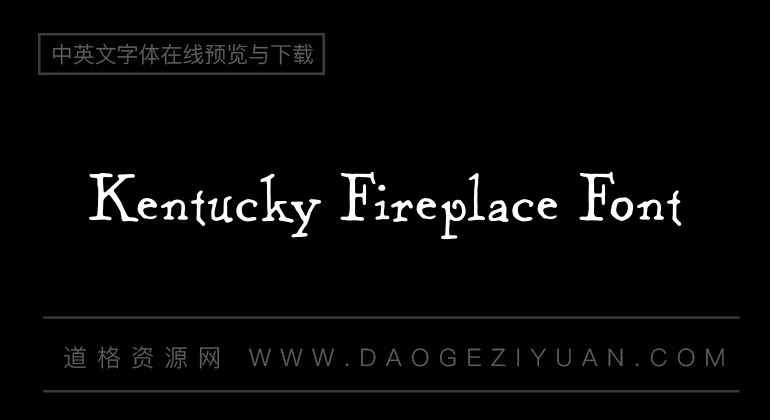
Kentucky Fireplace Font
Kentucky Fireplace Font 是一款受美国肌肉车文化启发的字体,它的设计灵感来自于 20 世纪 60 年代和 70 年代的铁路和车站招牌,以及美国 West Coast 的冲浪文化和摩托车文化。 这款字体具有强烈的手写风格和个性化的特点,字母间距较小,字母形状较为扭曲,让整个字体看起来更加生动有趣,适合用于宣传海报、标志设计和子标题等场合。它包含大写字母、数字和标点符号,共 127 个字符。 Kentucky Fireplace Font 可以在多种设计中使用,例如商标设计、海报广告、品牌推广等。它的使用会让设计作品更加独特个性化,给人留下深刻的印象。
Kentucky Fireplace Font是一款非常不错的手写艺术字体,具有很好的视觉感,适合于文化类的宣传设计、商业类品牌的广告和产品包装设计以及个性化文字排版等较多场景。